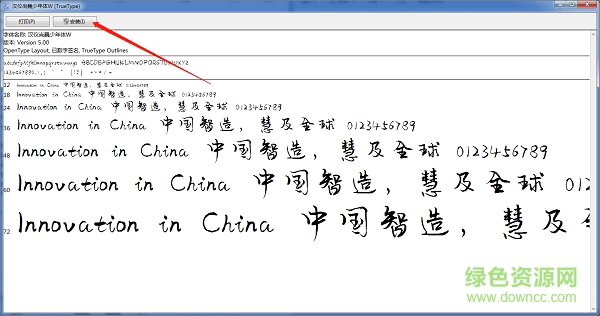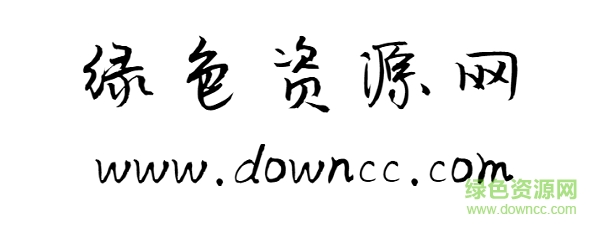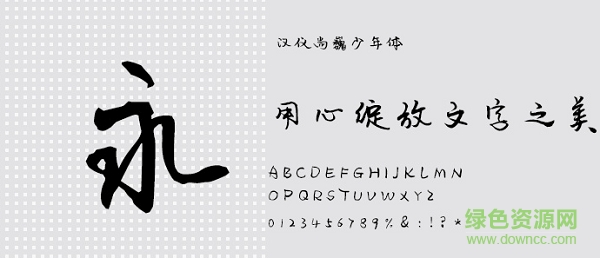
漢儀尚巍少年體w
漢儀尚巍少年體w是一款非常飄逸的字體,字體纖細(xì)唯美,簡(jiǎn)單的筆畫依然能夠勾勒出精彩的字體結(jié)構(gòu),可用于多個(gè)不同的字體排版,需要的用戶快來(lái)綠色資源網(wǎng)下載吧!
漢儀尚巍少年體簡(jiǎn)介:
漢儀尚巍少年體字體為手寫字體,既有行書(shū)的隨意灑脫之韻味,也有楷書(shū)的清晰筆鋒,無(wú)論是簡(jiǎn)體還是繁體排版使用都能狗給人更加舒適的感覺(jué),適用于版面的設(shè)計(jì)以及其他的作品之中!
漢儀尚巍少年體預(yù)覽:
漢儀尚巍少年體w